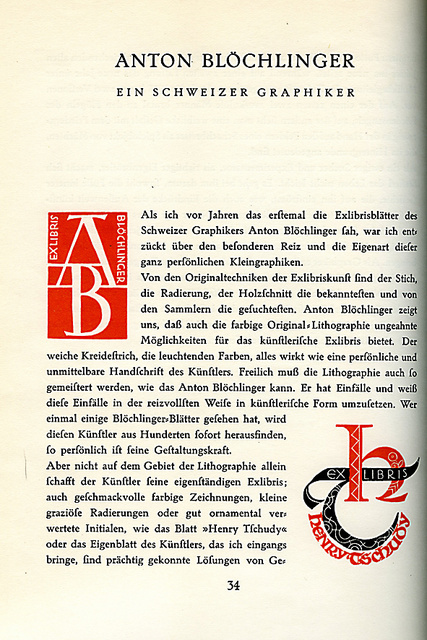
Neue Rechtschreibung?
Na, dann doch gleich
Maŗ und Morik
:-)
Wie soll denn eine Glyphe, die historisch falsch aber faktisch richtig interpretiert wird
Oh, müsste es hier nicht richtig heißen:
...eine Glyphe, die historisch RICHTIG ist, aber faktisch doppelt FALSCH interpretiert wird (sowohl vom schreibenden als auch vom lesenden) ...
Etwas falsches wird nicht allein dadurch richtig, nur weil es alle falsch machen. Dann werde ich wohl bald auch so etwas sehen:
Nur weil so einige Glyphen neu interpretiert werden können, wie man es gerade mag.
Warum sollte es der Gebrochenen anders ergehen als dem Griechischen und Kyrillischem?
Etwas falsches wird nicht allein dadurch richtig, nur weil es alle falsch machen.
Doch, genau so ist es, zumindest wenn es um Konventionen geht. Wörter, Buchstaben, Piktogramme etc. sind Symbole, die immer genau für die Bedeutung stehen, die die Mehrzahl der Nutzer ihnen zuschreiben – auf die man sich also gemeinschaftlich geeinigt hat.
Woher kommt denn die tz-Ligatur? Hat das göttliche Ministerium für Buchstaben diese Form für die gesamte Lebenszeit des Universums verordnet? Nein, es ist eine Konvention. Nicht weniger, aber auch nicht mehr. Mit den Wörtern »richtig« und »falsch« muss man im Zusammenhang mit Konventionen sehr vorsichtig sein.
Woher kommt denn die tz-Ligatur? Hat das göttliche Ministerium für Buchstaben diese Form für die gesamte Lebenszeit des Universums verordnet?
Na gut, dann werde ich mich nächstes mal, wenn ich Berlin besuche zum Bersarinplak, Ecke Petersburger Strake fahren lassen...
Hat irgendjemand behauptet, dass die Belegung des oben genannten Freefonts eine etablierte Konvention wäre? Ich habe nur vom Prinzip™ der Konventionen an sich gesprochen. Und die basiert eben nun mal nicht auf der Tunnelblick-Denke der Konservativen, dass die Konventionen, mit den man selbst am meisten vertraut ist, ihrem Wesen nach eine für allzeit gültige »Richtigkeit« besäßen.
Wörter, Buchstaben, Piktogramme etc. sind Symbole, die immer genau für die Bedeutung stehen, die die Mehrzahl der Nutzer ihnen zuschreiben …
Und diese Bedeutungen haben sich immer geändert und werden sich auch weiterhin ändern.
Wie du meinst...
Dann werde ich auch diesen schönen neuen Buchstaben, den ich da in meiner Schrift drin habe auch so anwenden, wie andere diesen noch recht unbekannten Buchstaben möglicherweise lesen könnten, auch wenn es da so ein paar Konventioinsfetischisten gibt, die darin ein großes ß sehen wollen:
ẞRATWURST und ẞUTTERẞROT
und schon hab ich ein schickes neues B ;-)
OK, hier in dieser Schrift sieht es nicht so B-mäßig aus, aber in anderen Schriftarten kann ich es gut benutzen:
Wie gesagt: es hat keiner behauptet, dass man solche tz-k benutzen SOLL oder dass das irgendwie gut und förderungswürdig wäre.
Es wurde lediglich darauf hingewiesen, dass deswegen die Welt nicht automatisch »verblödet« (siehe Phoibos’ Erklärungen) und dass die besagte »Richtigkeit« von Buchstaben so nicht existiert.
Bitte genau auf die Inhalte achten. Wenn man sich gegen bestimmte Argumente stellt, heißt das nicht automatisch, dass man das Gegenteil dessen möchte, worauf man sich bezieht.
OK, die Welt geht nicht unter. Trotzdem ist es eben falsch, auch wenn alle Welt den Text trotz allem versteht. So lange ich noch irgendwo recht oft eine tz-Ligatur als tz antreffe, bleibt es schlicht falsch, wenn ich es nebenher und durchaus auch als solches gelesen als k verwende.
Genau so wenig geht die Welt unter, wenn ich in meinem letzten Bilchen eben GROBSTADT lese...
Wenn man sich gegen bestimmte Argumente stellt, heißt das nicht automatisch, dass man das Gegenteil dessen möchte, worauf man sich bezieht.
Das nennt man »sauber denken«.
Das ist theoretisch ja korrekt. Praktisch legitimiert man durch solchen Libertinismus aber eben doch erwähnte Fehler — und fördert sie dadurch.
Ich habe noch sehr ungut in Erinnerung, wie die F.A.Z. einmal beschloß, daß die »klugen Köpfe«, die ja angeblich dahinterstecken sollten, zu dämlich wären, ein ſ zu lesen und fürderhin in den damals noch gotischen Kommentarüberschriften regelwidrig ein s schrieb, wo ein ſ hingehört hätte. Hier hatte man vorab ein Maß an Verblödung beschlossen, um es dann hernach selbst herzustellen, indem man Jungleser durch Falschschreibung verwirrte.
Hier hatte man vorab ein Maß an Verblödung beschlossen, um es dann hernach selbst herzustellen, indem man Jungleser durch Falschschreibung verwirrte.
nö. es war ein richtiger schritt um die jungleser (die in der schule nicht gesagt bekommen, dass es sich hierbei nicht um ein f handelt) zu verunsichern. ganz klarer wandel zur moderne, trotzt fraktur, ohne rücksicht auf 'alte' regeln die eh kaum einer richtig kennt. find ich zeitgemäß und richtig.
Dämmmaterial und Brennnessel fielen mir noch ein, aber da gab es "früher"TM ja diesen oft genutzten Querstrich (Makron) über dem m (und glaub auch über dem n), finde ich gerade nicht im Unicode (da wäre nach dem [sZ][/sZ] noch was zu tun ...)
Pappplakat, ... Hmmm ... Flanelllumpen, .... Die anderen Konsonanten kommen eher selten doppelt hinten vor?
Wahllos aus diesem Strang gezupft:
«Konventioinsfetischisten»,
«gleichmal», «Bilchen»,
«Schritttermpo»,
«Rechtschreibunf»,
«Zeitenossen» …
Neue Rechtschreibung?